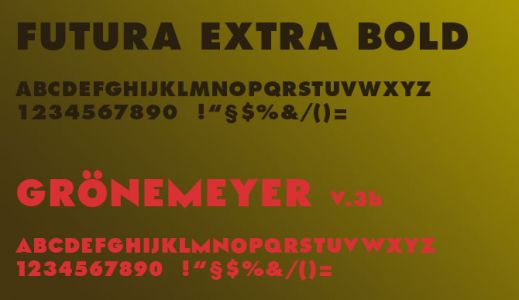
Schrift GRÖNEMEYER 12
also what the font weiß es nicht ;-), die Futura Black isses nich (M, N und Ö sind zu extravagant), dann dachte ich an die DTL Nobel ... Nix da, is zwar viel schöner, aber isses trotzdem nicht ...
Wisst ihr es???
Ich hab's rausgefunden: Es ist, wie ich aus vertraulicher Quelle weiß, eine Abwandlung der Futura Extra Bold extra :wink: für das Grönemeyer-Album. Zum Vergleich mal:
Nur für die Wortmarke Grönemeyer wurde dann noch das "Ö" verändert ...
ist ja auch ein ganz hübsches „typographisches“ CD-Booklet geworden.